2026為大家整理了最齊全、最多的的可商用字體下載!本站介紹過不少的中文字體下載資源,本篇則是整理免費可商用字體下載網站,支援可商用繁體中文、平假名、片假名、各種符號、日文、英文、與漢字中文字體。有可商用的可愛的手寫字體、圓體、漫畫風、藝術文字,風格非常多元~不用擔心侵犯版權問題,不過下載前還是建議先閱讀字體的授權相關說明哦。支援Windows,Mac安裝使用。更多免費字體:免費繁體中文字體下載。
1. 清松手寫體
清松手寫體是來自順其字然所開發的字體,可供個人與商業100%免費使用!共包含3款不同款式的可愛風字體免費下載安裝,完整的中文、英文、標點符號和數字字庫,不怕有漏字問題。
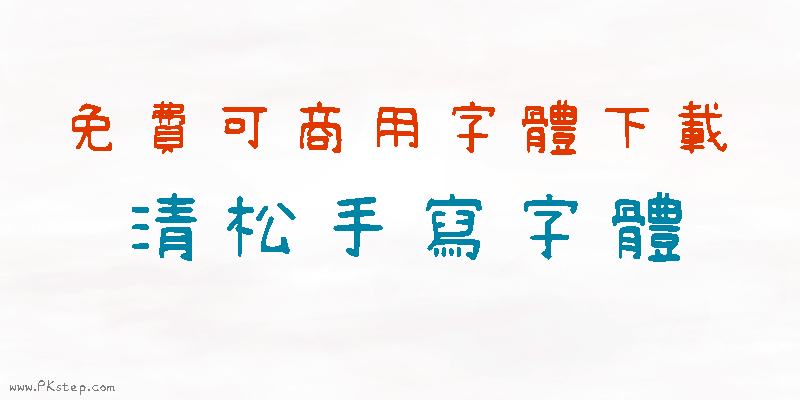
2. Taipei Sans TC 台北黑體下載
由翰字鑄造以思源黑體為基礎,投入的開源字型改作-台北黑體Taipei Sans TC,可供商用,非常完整的漢字庫:繁體中文、簡體字、日韓漢字。
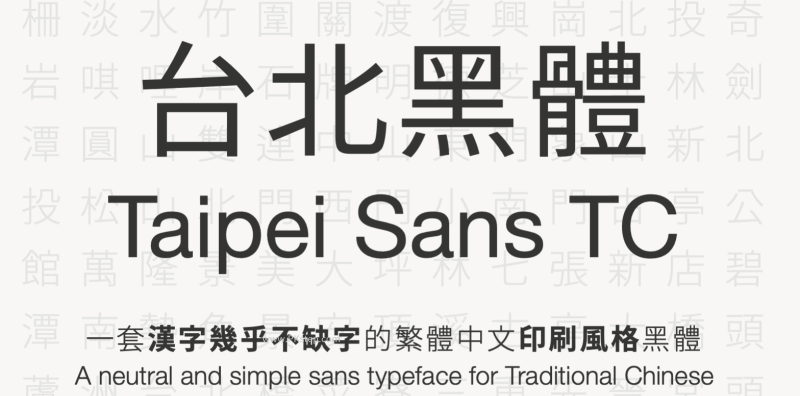
3. 獅尾字體
獅尾字體下載,由「Max的每一天」網站版主分享的字體,支援繁體中文、簡體中文、韓文與日文,可供免費商用
4. 俐方體11號下載
免費點陣圖字體下載,俐方體11號,可供商用,像素風的免費中文字型,套用在遊戲、影片或海報都非常有質感。
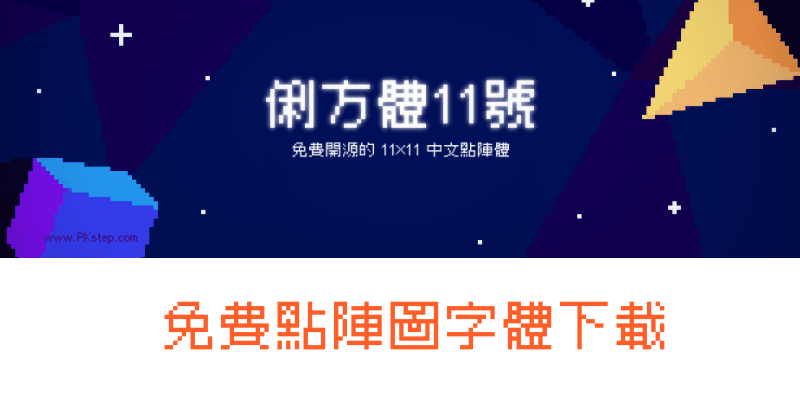
5. 宅在家字體下載
宅在家字體,由網友創作的免費手寫風字體,可供個人與商用,包含宅在家字動筆、宅在家麥克筆,可愛和具有POP風格的字體,繁體中文字庫相當齊全,幾乎沒什麼漏字,英文、數字、日文也都能套用,
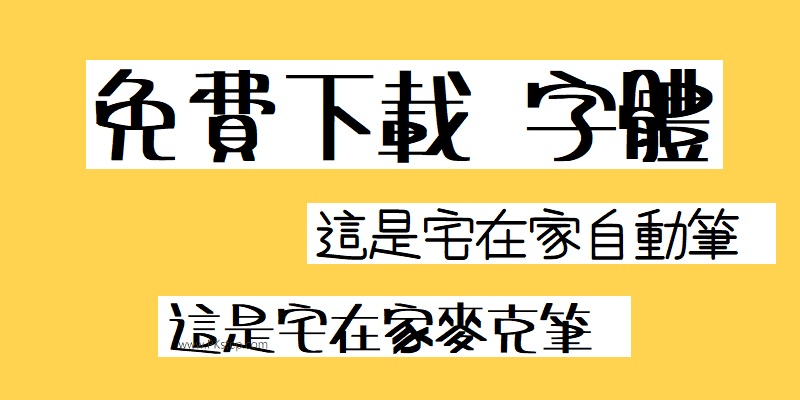
6. 免費書法字體下載
免費書法字體下載,由日本網站武藏推出的具有中國風的毛筆字體,共6款可免費下載,包含青柳、橫山毛筆、草書、行書、隸書等…雖然是日本的字體,但繁體中文也能套用,部分可能會有缺字。
7. kawaii 手書字體
kawaii手書字體,可免費商業使用,比較可惜的是收錄的中文字比較少,但猶如字體名稱一樣,非常卡哇伊!
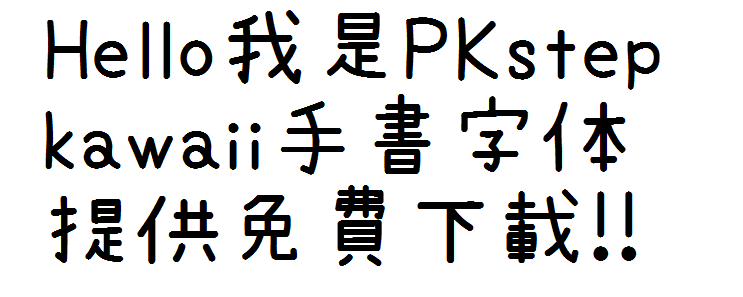
8. irohamaru 哥特字體下載
來自MODI工廠的irohamaru哥特字體,稍微偏圓的字型樣式,支援日文平假名、片假名、數字符號、英文、中文字體也收錄滿多的,漏字問題比較不那麼嚴重,個人/商業使用都是允許的。
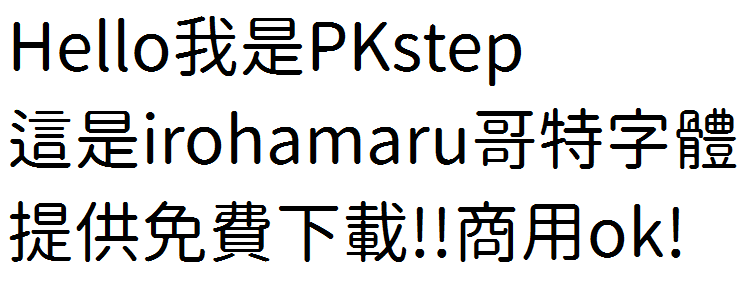
9. Rii 可愛字體免費下載
Rii Font設計的Rii pop corner手寫、Riteki和、Riteshiki N三種免費字體下載,收錄的漢字也非常多,可愛又有藝術感。
10. mushin 手寫字體免費下載
來自MODI工廠的mushin手寫字體,可商業使用,mushin收藏的漢字非常多,可愛的手寫風字體,應用在海報或文宣設計都超加分!
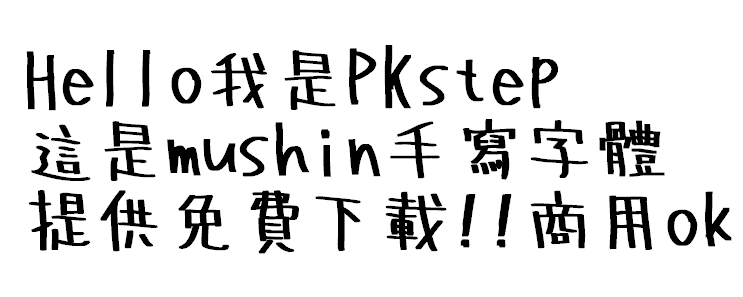
11. Iroha Kaku Classi 字體下載
來自MODI工廠的Iroha Kaku Classi哥特字體免費下載,支援漢字、英文、數字符號與日文平假名/片假名,允許商業與個人自由使用。
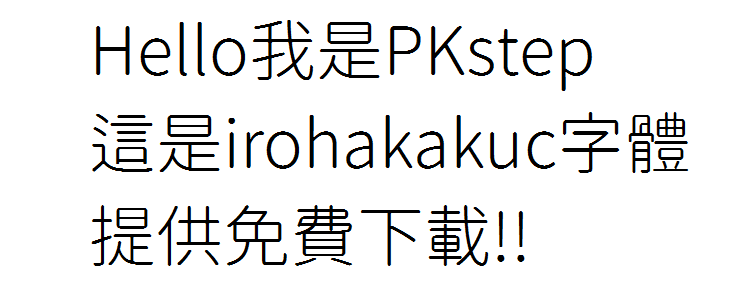
12. Line Font 超級細字體
Line Font提供的Ultrafine Gothic超級細字體,如果是要印刷出來的話,建議要注意是不是會因為字體過細導致看不到文字。
13. timemachine 時光機器字體
來自MODI所提供的timemachine時光機器字體,收錄日文、英文、中文免費可商用字體免費下載。
14. OmePlus P Gothic 青梅字體
OmePlus P Gothic青梅字體可商用字體,有三種不同的粗細字型,依照自己的喜好進行安裝。
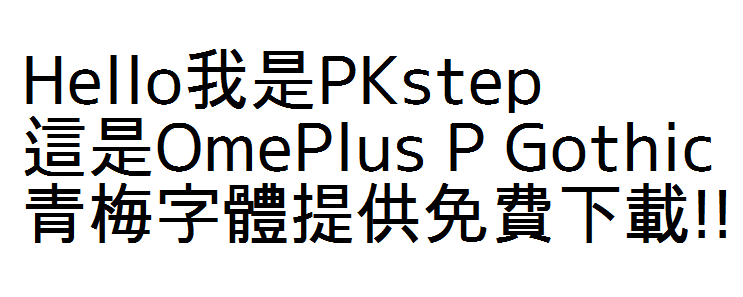
15. toroman 漫畫風字體免費下載
toroman字體–此字體並不支援中文漢字,但套用在英文字型是沒有問題的!因為覺得非常有特色的個性字體,因此也在此推薦給大家。
16. FontBear 免費字體下載
17. Google 思源黑體下載
Adobe與Google所領導開發的開源字型-Google思源黑體、思源宋體、思源柔黑體。
18. 站酷字體下載
站酷字體免費下載,提供8款藝術中文字體,可供商用,有藝術中國風的字體、娃娃體、少女體、布丁體風格的字型。
19. 100font 免版權字體下載
專門整理可商用字體的網站-100font免版權字體下載網站。